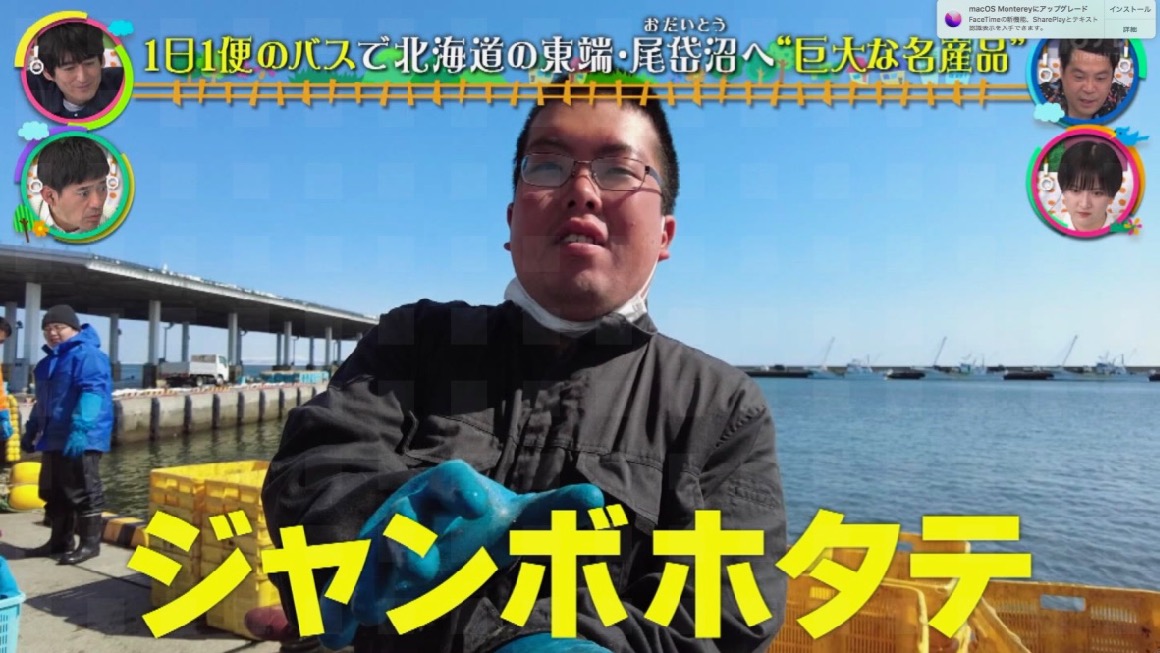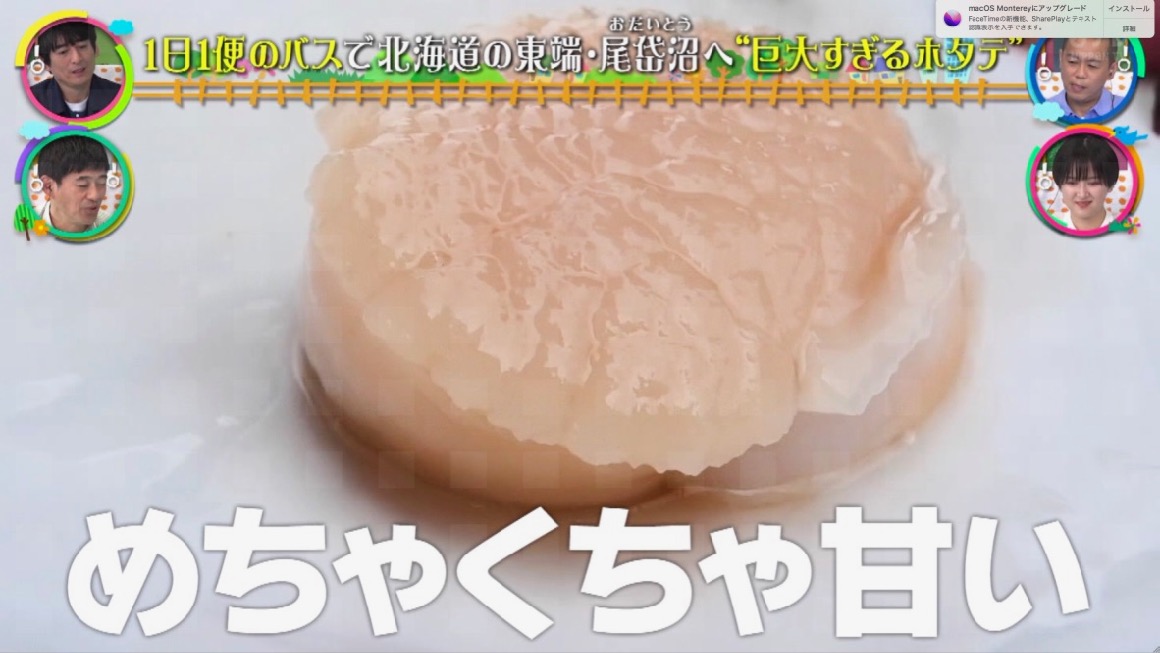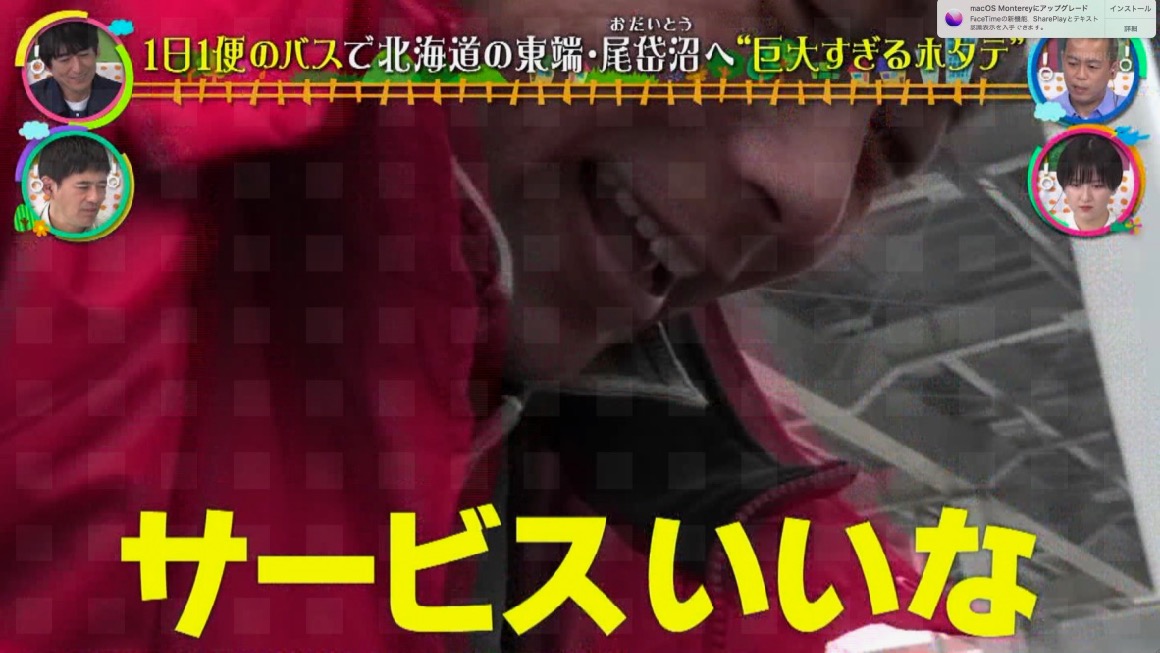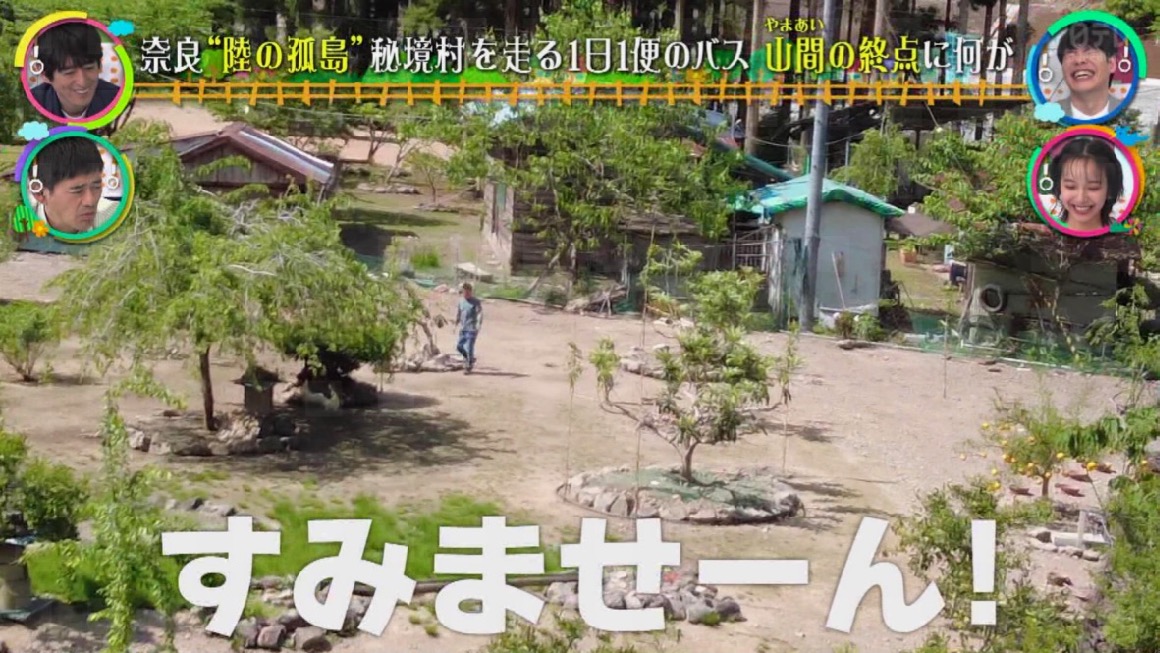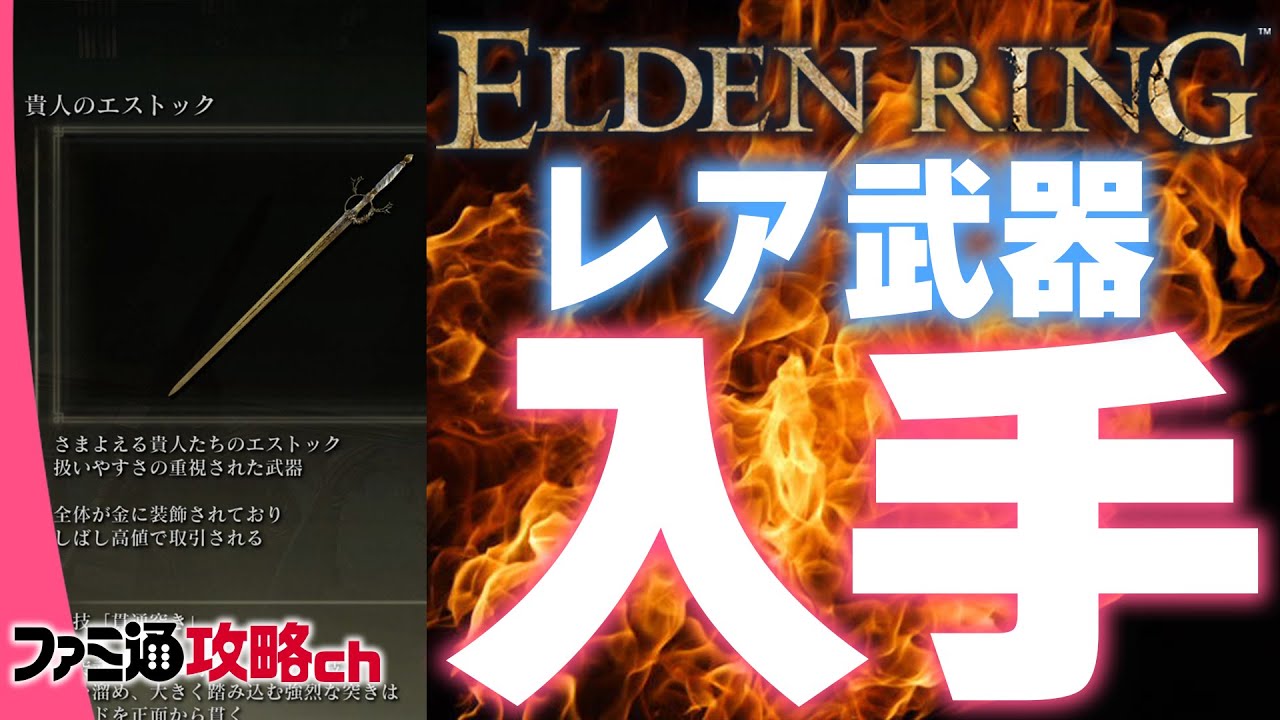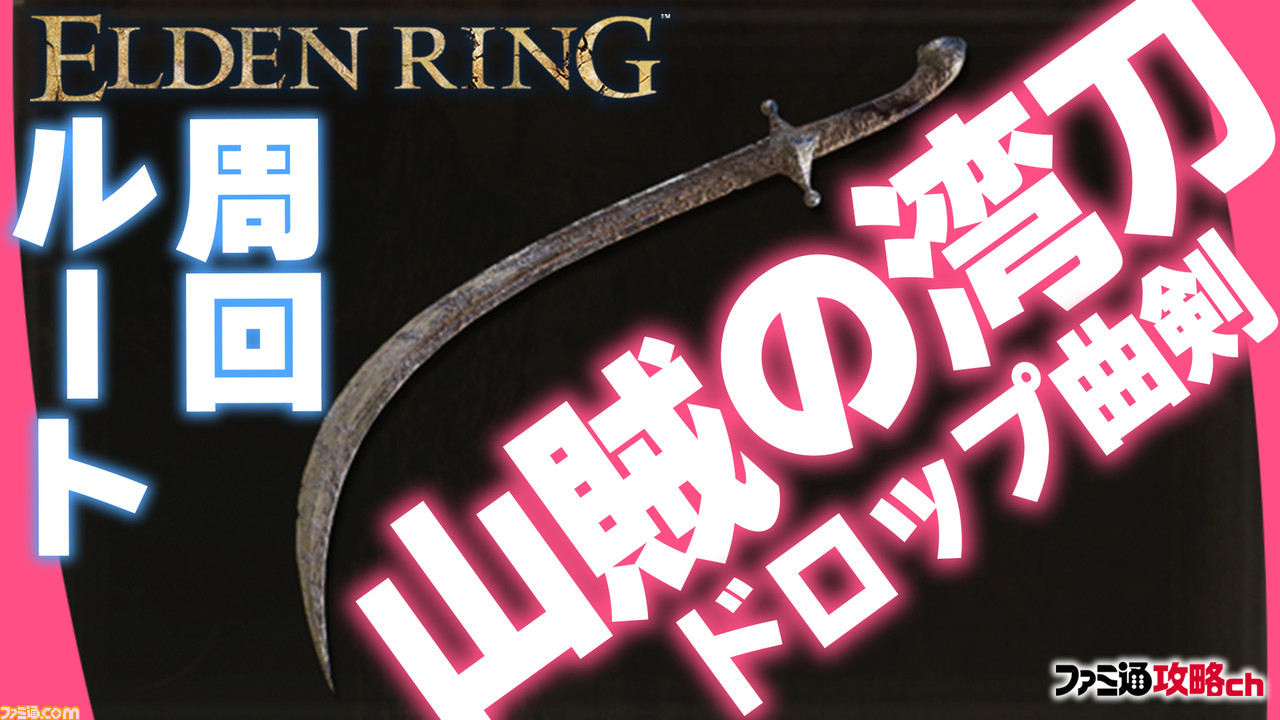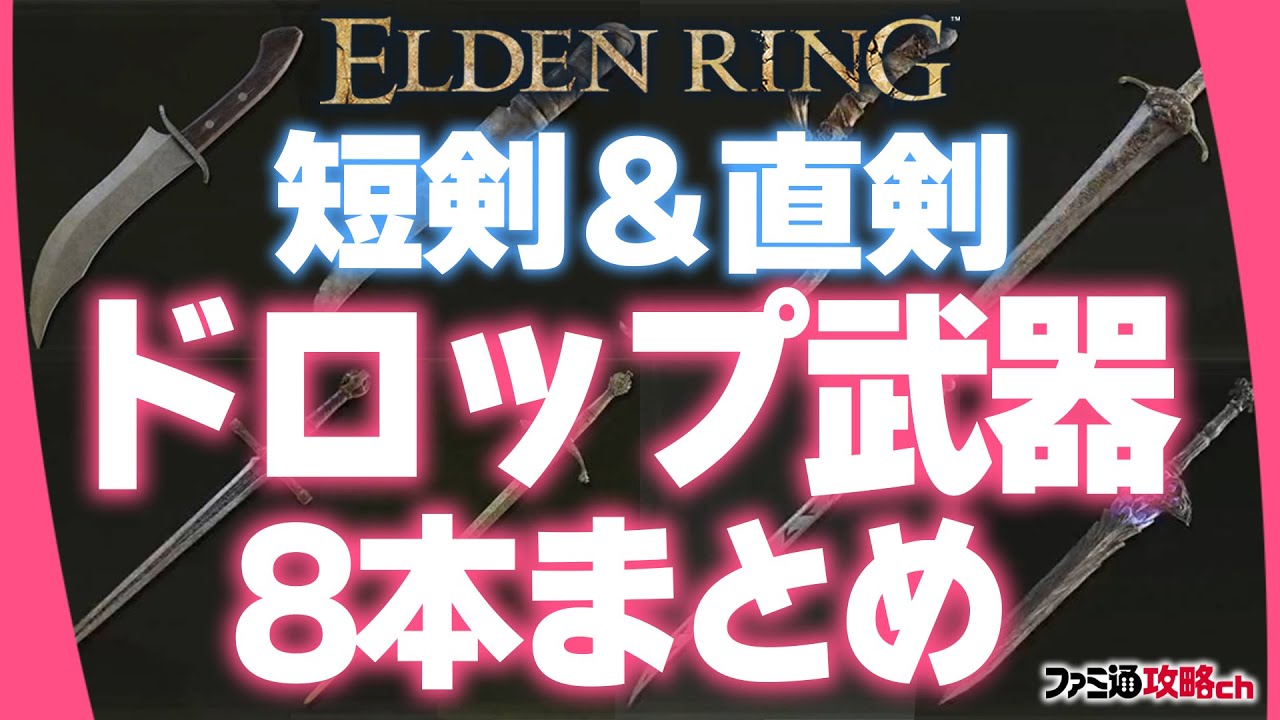
本の表紙 さとうゆたか
中公文庫コミック版「はだしのゲン」。
デジタルフォントではなく、写植文字盤の文字が使われている気がする。
もう1点。
あ さとうゆたか
本日の新聞広告。
これも さとうゆたか
新聞広告。
横組のタイトルはデジタルフォント。
商品の装丁は、写植で印字されたアナログ文字が使われている。
キャンペーン さとうゆたか
丸井がやっているエポスカードの優待キャンペーン。
「兎田ぺこら」とのコラボレーション企画。
合計の「計」のごんべんを見れば、ここで使われているフォントが「わんぱくルイカ」だと分かる。
ファミマで さとうゆたか
ウマ娘 プリティーダービーとのコラボ商品。
新聞広告 さとうゆたか
今朝の読売新聞。
オリックス生命の広告。
太く大きな文字すべてに「わんぱくルイカ」が使われている。
使用ウェイトが08なので、もしかするとAdobeFontsを利用してるのかも…
本の表紙 さとうゆたか
書名:みんなでかぞえる なんばーず!
著者:マグダ・ガルグラコヴァ、マリー・ウルバンコヴァ
発行:大日本絵画
映画クレヨンしんちゃん×大阪メトロ takumi
まもなく公開される映画「クレヨンしんちゃん」と大阪メトロのコラボ企画の広告。
「わんぱく」フォントが使われています。
わんぱくフォントが使われている部分を拡大。
この小さな文字の部分ですね…。
テレビ番組 さとうゆたか
フジテレビ「なりゆき街道旅」
本の表紙 さとうゆたか
署名:アンパンマンとにらめっこ!
著者:やなせたかし、トムス・エンタテインメント
発行:フレーベル館
本の表紙 さとうゆたか
署名:パウ・パトロール ミッションに ちょうせん!
発行:小学館
FXの会社 takumi
外為ファイネストのTwitterアカウント。
画像に「わんぱくルイカ」が使われています。
このウェイトはAdobeFontsかも…。
公式サイトに掲載の画像にも使われているようです。
こういう投資関係の広告に、AdobeFontsのタイプラボフォントが使われだしましたね…。